和文と欧文を別フォントで設定できる「合成フォント」。
和文は明朝体、欧文はセリフ体やサンセリフなど異なる書体を組み合わせることで、可読性とデザイン性を両立できます。
今回は、明朝体ベースのおすすめ組み合わせ6選をご紹介します。
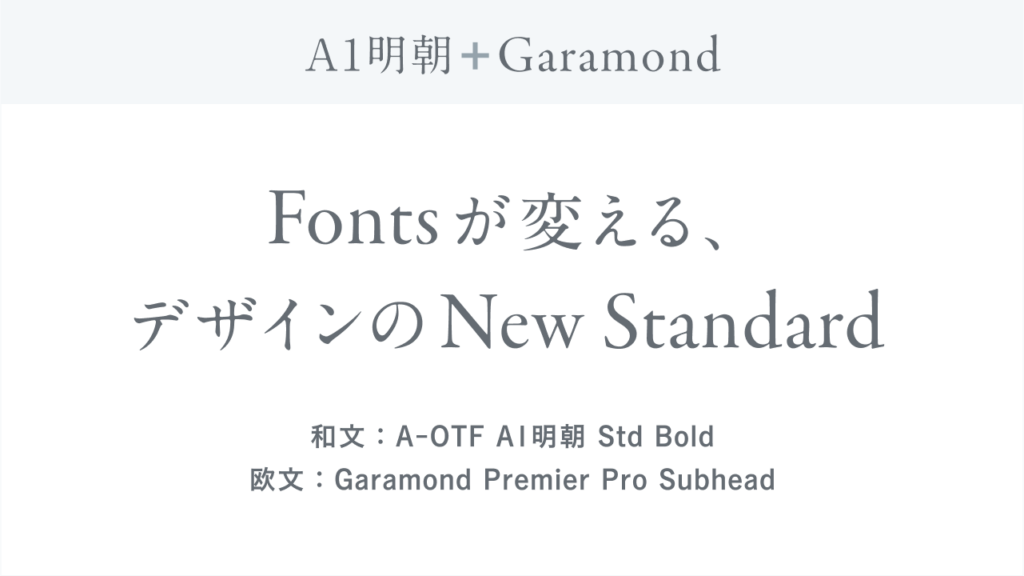
A1明朝の端正な線に、Garamondのクラシカルで柔らかい曲線が合わさり、知的で落ち着いた雰囲気に仕上がります。高級感のあるデザインに最適です。
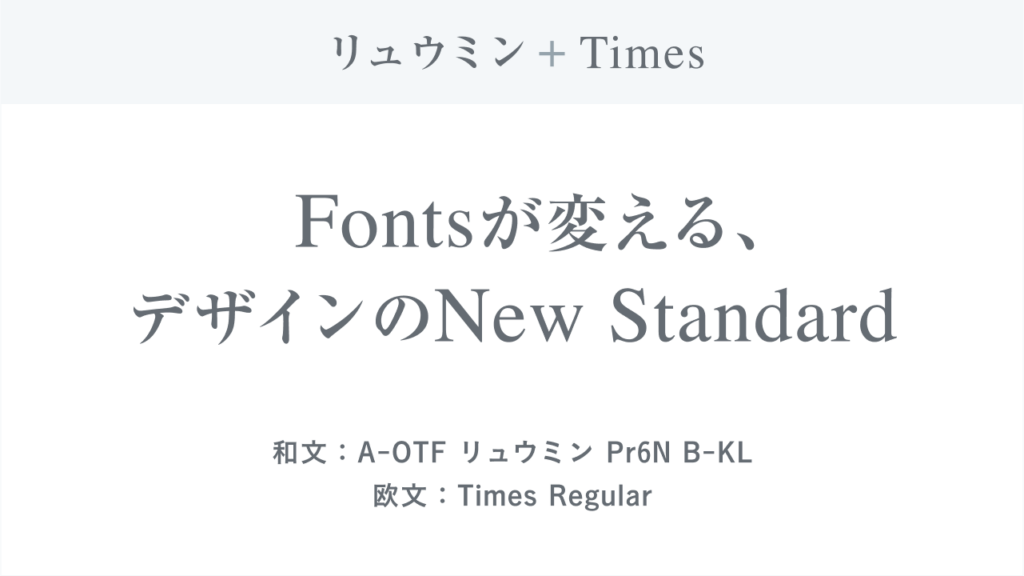
新聞や書籍で長く使われてきたリュウミンに、読みやすさと格式を備えたTimesを組み合わせることで、格調高くフォーマルな印象になります。
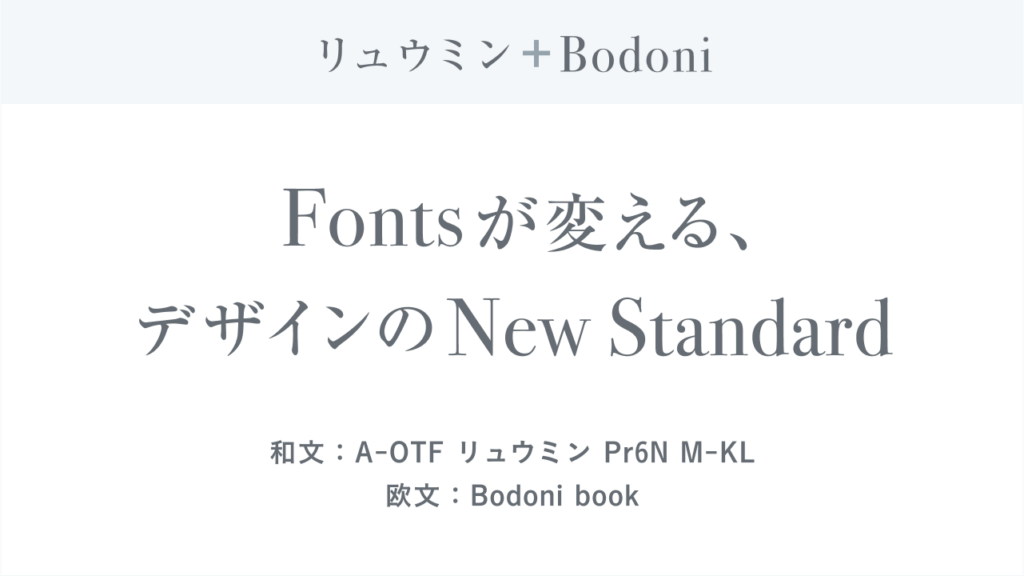
安定感のあるリュウミンに、強いコントラストと直線的なセリフが特徴のBodoniを合わせると、クラシカルでありながら華やかさのある見た目に。
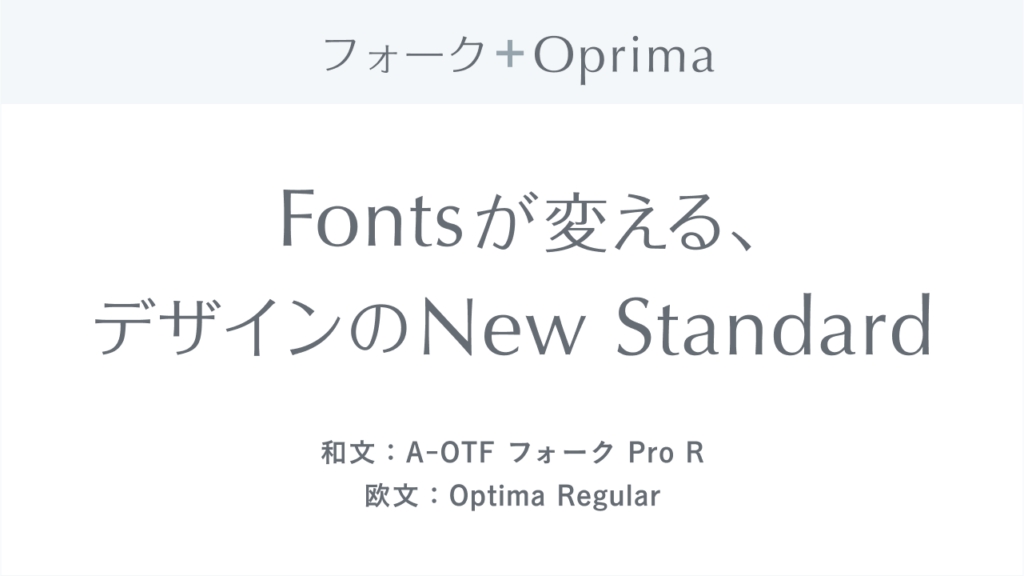
モダンな印象のフォークに、洗練された欧文書体Oprimaを合わせることで、すっきりと現代的な雰囲気に。パンフレットやWebデザインに向いています。
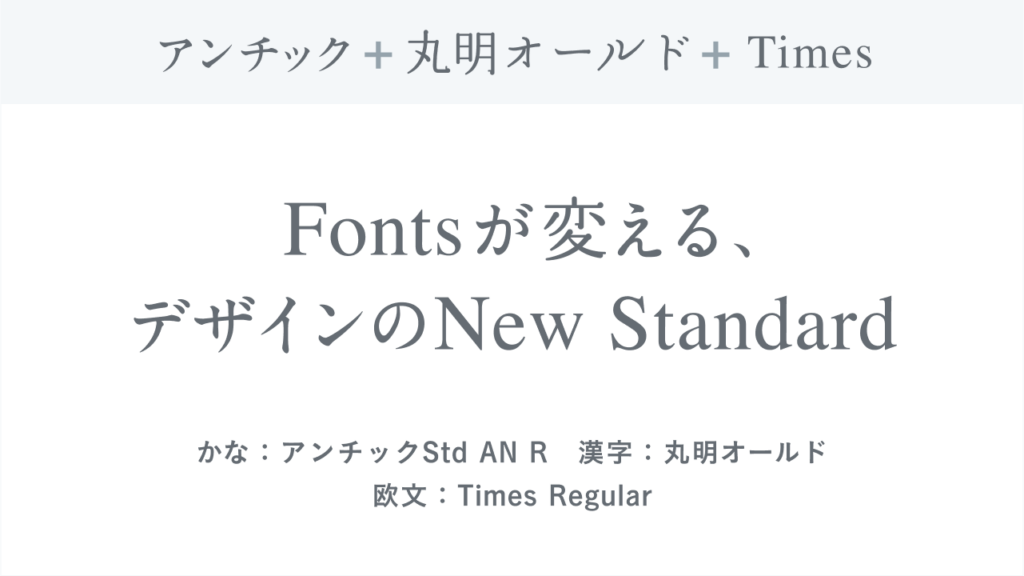
かなに力強いアンチック、漢字は柔らかい丸明オールド、欧文に知的なTimesを組み合わせることで、親しみやすく読みやすい中にも落ち着きのある雰囲気になります。
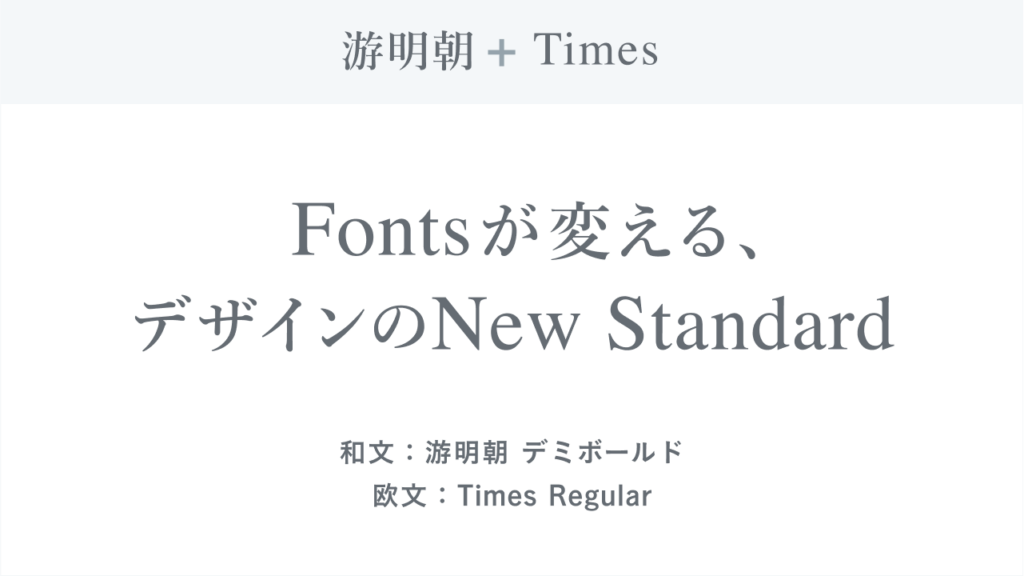
美しいプロポーションの游明朝と、無料で使えるTimesを組み合わせることで、上品で汎用性の高い組み合わせに。印刷物からWebまで幅広く活用できます。
合成フォントは、和文と欧文の相性を意識して選ぶことで、文字だけで世界観を表現できます。
ストロークの太さや文字の高さ、雰囲気を揃えることが、洗練されたデザインへの近道です。